Flattersatz
Ein »Flattersatz« ist eine Schriftsatzart. In der Typografie wird zwischen asymmetrischen und symmetrischen Flattersatz unterschieden. Ein »Asymmetrischer Flattersatz« ist ein Flattersatz mit linksbündiger oder rechtsbündiger Satzausrichtung, also ein ungleichmäßiger Flattersatz, beispielsweise ein Rauhsatz. Der »Symmetrische Flattersatz« hingegen ist ein gemittelter, gleichmäßiger Flattersatz. Er wird deshalb auch als »Axialsatz« oder »Zentrierter Satz« bezeichnet.
Etymologisch rühren die Begrifflichkeiten von altgr. »a« für »nicht« und »symmetria« für »Ebenmaß« zu »symmetros« für »gleichmäßig« bzw. »an« für »wider« oder »nicht« und altgr. »axis« für »Achse« her. 1)
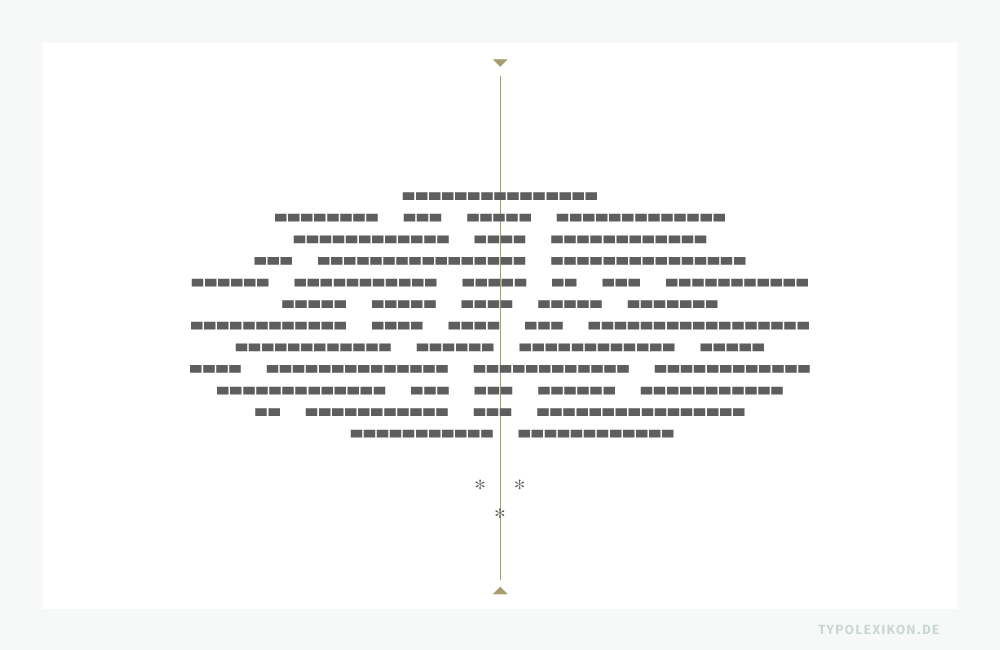
Asymmetrischer Flattersatz kann über eine linksbündige oder rechtsbündige Satzausrichtung verfügen. Im deutschsprachigen Werksatz versteht man unter Flattersatz vordergründig den Flattersatz mit einem Zeilenfall, bei dem alle Zeilenanfänge linksbündig, in senkrechter Satzausrichtung untereinander stehen, während die Zeilenenden frei auslaufen.
Nach dem Typografen und Lehrer Philipp Luidl (1930–2015) ist der Rauhsatz und der Blocksatz eine epische, der Flattersatz und der Gedichtsatz eine lyrische Schriftsatzart. 2) Je nach Aufgabenstellung und ästhetischer Betrachtungsweise werden Schriftsatzarbeiten in unterschiedliche Flattersatztechniken implementiert. 3)
Flattersatztechniken
Flattersatz
Flattersatz mit natürlicher Flatterzone und wenigen Silbentrennungen. Die Wortzwischenräume sind gleich. Die Zeilenlängen ergeben sich formal nach rhythmischen Gesetzen, also durch einen natürlichen Zeilenumbruch.
Englischer Flattersatz
Flattersatz mit natürlicher Flatterzone ohne Silbentrennung. Die Wortzwischenräume sind gleich. Die Zeilenlängen ergeben sich formal nach rhythmischen Gesetzen, also durch einen natürlichen Zeilenumbruch. 4) 5)
Rauhsatz
Allograph »Rausatz«. 6) Flattersatz mit häufigen Silbentrennungen, der die gesamte Satzbreite eines Satzspiegels bzw. einer Kolumne effektiv nutzt. Im Gegensatz zum Flattersatz ist die Flatterzone deutlich kleiner und die Anzahl der Silbentrennungen erheblich höher.
Die Wortzwischenräume sind gleich, der Zeilenumbruch erfolgt in der Regel primär durch kurze und häufige Silbentrennungen, wobei auch fünfbuchstabige Wörter getrennt werden (vor der Trennung zwei, nach der Trennung drei Buchstaben) und mehrere Trennungen untereinander folgen können. Je kürzer eine Flatterzone bzw. der Trennbereich ist, desto mehr (und kürzere) Silbentrennungen sind die Folge.
Handkorrigierter Rauhsatz
Flattersatz mit einer exakt definierten Flatterzone, welche im Satzspiegel bzw. im Umbruchsystem eines Gestaltungsrasters dokumentiert wird. In Desktop Publishing Software, beispielsweise InDesign® von Adobe® oder QuarkXpress® von Quark®, kann diese Flatterzone mit einer Hilfslinie oder als Trennbereich gekennzeichnet werden.
Der Zeilenumbruch wird mikrotypografisch individuell per Hand nachbearbeitet. D.h., die Zeilenlängen werden durch manuelle Silbentrennung, Manipulation der Laufweite, des Schriftgrads und der Wortzwischenräume zu einem bewusst geformten Rauhsatz strukturiert. Jedes Wort, dass sich innerhalb der Flatterzone (bzw. außerhalb der Hilfslinie) befindet, wird in der Regel getrennt oder ausgetrimmt.
Der handkorrigierte Rauhsatz hat seinen Ursprung in der Kalligraphie und ist der Vorläufer des Blocksatzes. Aus ästhetischer Sicht ist ein handkorrigierter Rauhsatz nur bei kurzen Satzbreiten, beispielsweise bei sehr schmalen Satzspalten in Zeitungen, empfehlenswert.
Schweizer Rauhsatz
Handkorrigierter Rauhsatz, der aufgrund seiner geringen Flatterzone – in der Regel unter 5% – schon beinahe wie ein schlecht ausgeschlossener Blocksatz aussieht. Wurde insbesondere in der ideologisierten Schweizer Grotesk-Typografie der 1950er bis 1980er Jahre verwendet, die sich in der Tradition eines »antifaschistischen« Bauhausstils verstand.
Gedichtsatz
Flattersatz ohne Silbentrennungen, bei dem der Umbruch sprachlich durch den Autor*in vorgegeben ist, beispielsweise bei Gedichten.
Dramaturgischer Flattersatz
Flattersatz mit und ohne Silbentrennung, bei dem der Umbruch teils an einer bestimmten Stelle durch eine Dramaturgie, beispielsweise bei Dialogen in einem Drehbuch, vorgegeben ist.
Axialsatz
Symmetrischer Flattersatz, dessen Zeilenmitte exakt an der Mittelachse einer Seite bzw. einer Kolumne ausgerichtet ist (siehe Axialsatz).
| ↑1 | Anmerkung: In der Paläografie und in älteren typografischen Lehrbüchern, z.B. des deutschen Typografen und Schriftgelehrten Jan Tschichold (1902–1974), wird der Asymmetrische Flattersatz deshalb auch als »Anaxialer Flattersatz« bezeichnet. |
| ↑2 | Quelle: Luidl, Philipp: Typografie, Herkunft, Aufbau, Anwendung. Schlütersche Verlagsanstalt und Druckerei, Hannover, 1984, ISBN 3–87706-212–1, Seite 82. |
| ↑3 | Literaturempfehlung: De Jong, Ralf und Friedrich Forssman: Detailtypografie, Verlag Hermann Schmidt, Mainz, ISBN 978-3-87439-642-4. |
| ↑5 | Anmerkung: Der Begriff »Englischer Flattersatz« stammt aus dem gewerbespezifischen Vokabular deutscher Typografen des 19. und frühen 20. Jahrhunderts. Ähnlich wie der Begriff »Englische Typografie« steht er für eine angelsächsisch geprägte Antiqua-Schriftkultur. |
| ↑6 | Anmerkung: »Rauh« ist die ursprüngliche Schreibweise von »rau«, einem Synonym für »ruppig, rüpelhaft und roh«. Seit der deutschen Rechtschreibreform von 1996 wird Rauhsatz auch ohne »h« geschrieben. |